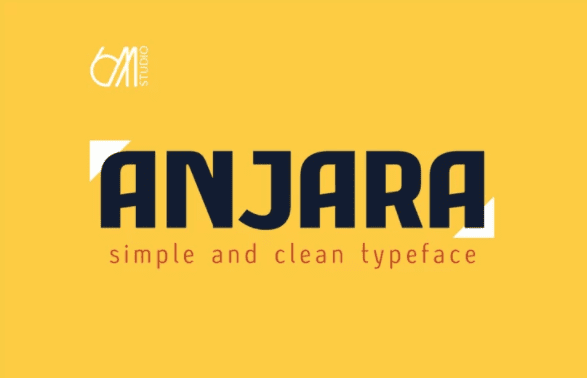
[Fontbundles] Anjara Font (2021)
Название: Anjara Font (2021)
[Fontbundles] Anjara Font (2021)
Этот шрифт получил свое название от слова "anyar", что на местном индонезийском (яванском) языке означает "новый/современный".
Как и его название, этот шрифт придает ему современный и простой вид.
Благодаря средней контрастности Anjara легко выделяется в любых композициях, особенно в жирной версии.